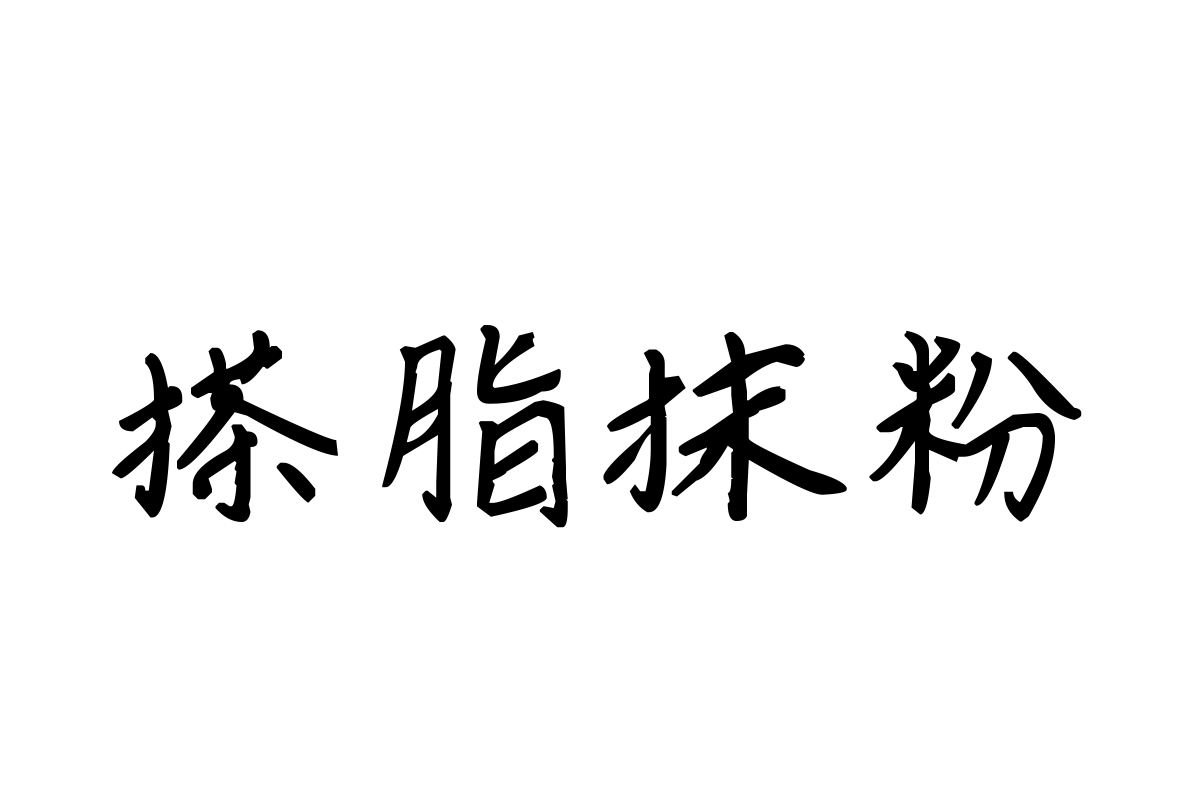
“米开最亲爱的你”是一款由设计师米开设计,以中文字体为载体的创意字体。这款字体以其独特的设计风格和丰富的表现力,深受广大用户的喜爱。以下是对这款字体的介绍:
1. 设计风格:米开最亲爱的你是一款具有现代感和时尚气息的中文字体。它的字形线条流畅,结构紧凑,给人一种简洁明快的感觉。同时,这款字体在细节处理上也相当精致,如笔画的粗细变化、字间距的调整等,使得整体视觉效果更加和谐统一。
2. 适用范围:米开最亲爱的你适用于各种需要展示中文字体的场景,如广告设计、品牌标识、海报设计、网页设计等。无论是在商业还是艺术领域,这款字体都能展现出其独特的魅力。
3. 使用效果:使用米开最亲爱的你字体,可以有效地提升设计作品的整体质感和视觉效果。它的线条流畅,结构紧凑,能够很好地传达出文字所要表达的情感和意境。同时,这款字体的可读性也很好,即使在较大的尺寸下也能保证清晰可见。
4. 适用人群:米开最亲爱的你字体适合各类设计师使用,尤其是那些喜欢尝试新颖、独特风格的设计师。同时,对于从事广告、品牌设计等相关领域的专业人士来说,这款字体也是一个很好的选择。
总之,米开最亲爱的你是一款极具个性和创意的中文字体,无论是在设计作品中还是在日常应用中,都能展现出其独特的魅力。
米开最亲爱的你